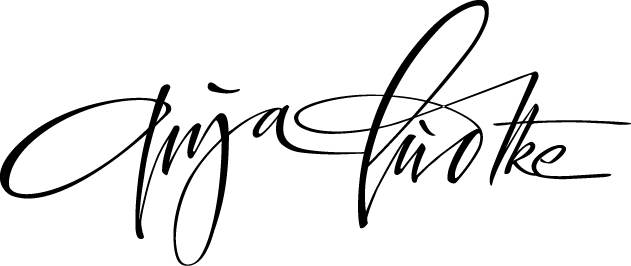
Le Geste fait Signe
Internationale Kalligrafie-Ausstellung in Frankreich
Erläuterungen des Veranstalters Florian Besset zum Thema
« Le Geste fait Signe »:
Auf Französisch ein doppelsinniges Wortspiel. Le geste fait signe: (fait signe: zum Zeichen gemacht) Die Geste wird zum Zeichen, einerseits. Le geste fait signe (faire signe = ansprechen): Die Geste welche, durch ihre Konkretisierung in der Form eines Zeichens, anspricht, aussagt und bewegt, andererseits. Und dies über die Lesbarkeit hinaus, oder trotz des “Verlustes” der Lesbarkeit. Auf den Spuren der Faszination welche es der westlichen Kalligrafie erlaubt, sich von der reinen Lesbarkeit zu befreien. Worin besteht die Faszination welche über die Lesbarkeit hinaus wirkt, über die primäre Funktion der Schrift hinaus, bis zum Übergang zur Malerei. Anne Zali z. B. drückt es folgendermassen aus: « Une exploration… « (…) dans l’épaisseur profonde d’un geste polyphonique, chantant, dessinant, qui déborde très largement la langue. » Meine bescheidene Übersetzung: “Eine Forschungsreise in der Dichte einer polyphonen Geste, singend, zeichnend, weit über die Sprache selbst.” Oder der Philosoph Roland Barthes: « L’illisibilité, loin d’être une défaillance, serait la vérité de l’écriture. » “Die Unlesbarkeit, weit von einem Versagen entfernt, wäre die eigentliche Wahrheit der Schrift.”